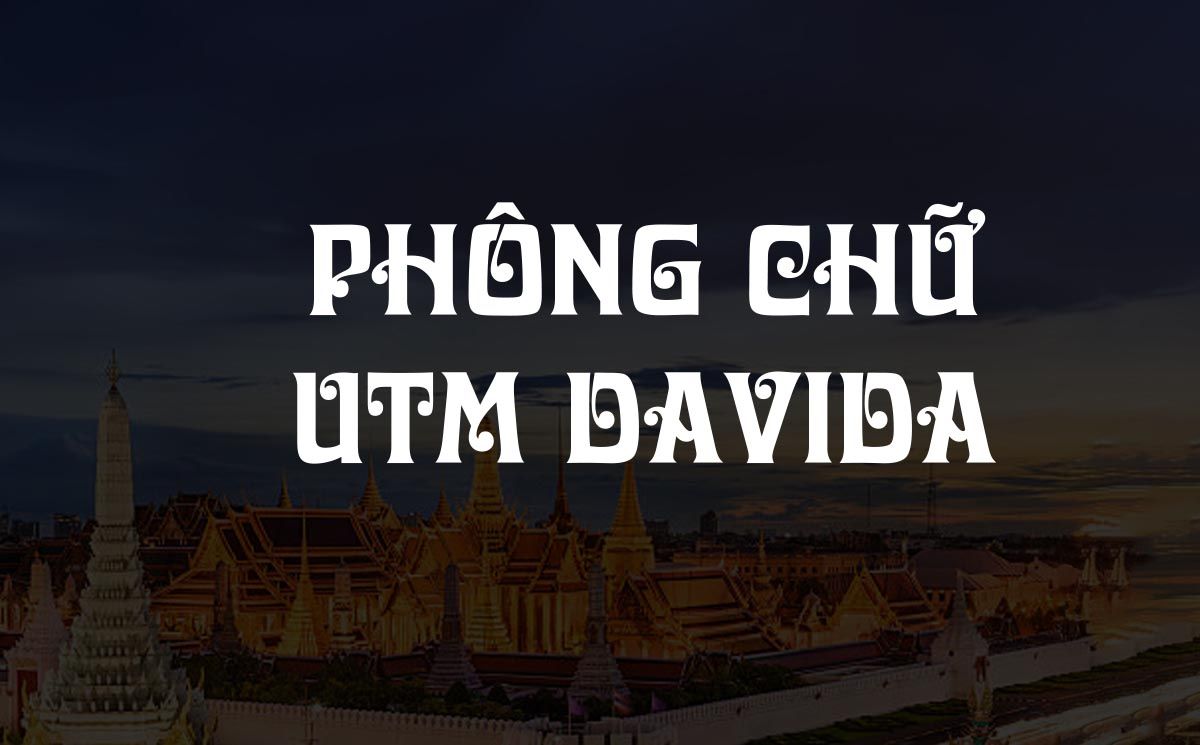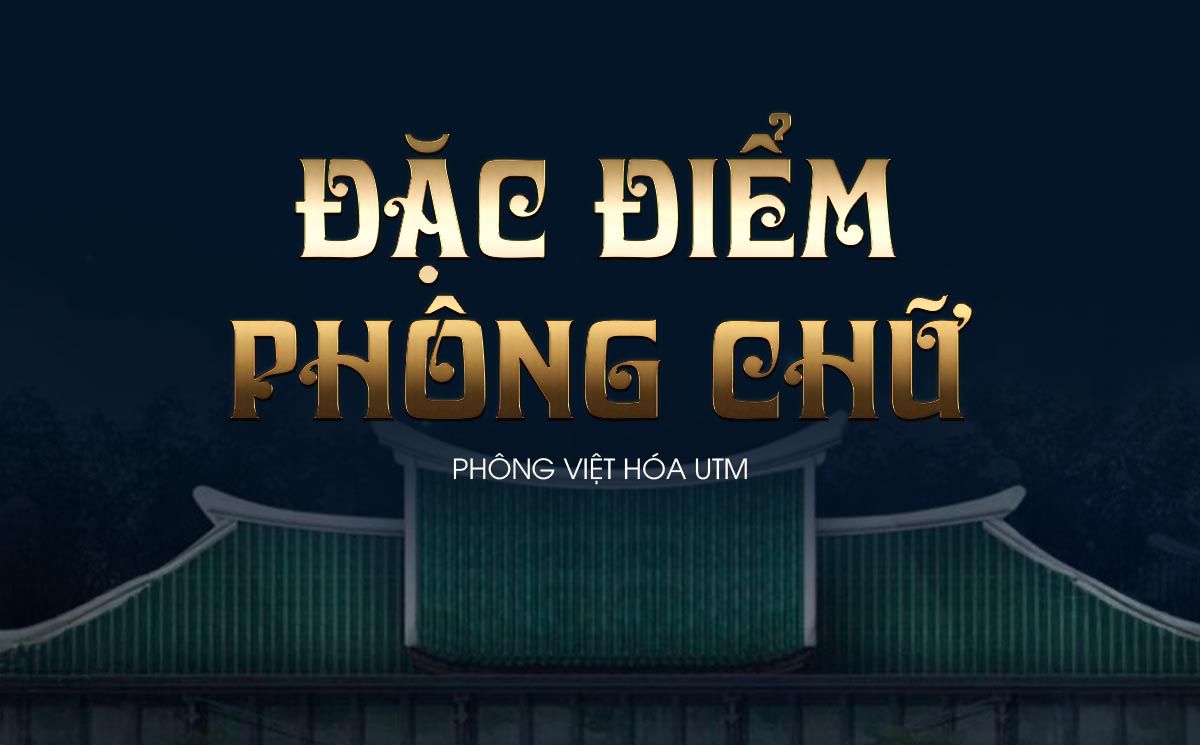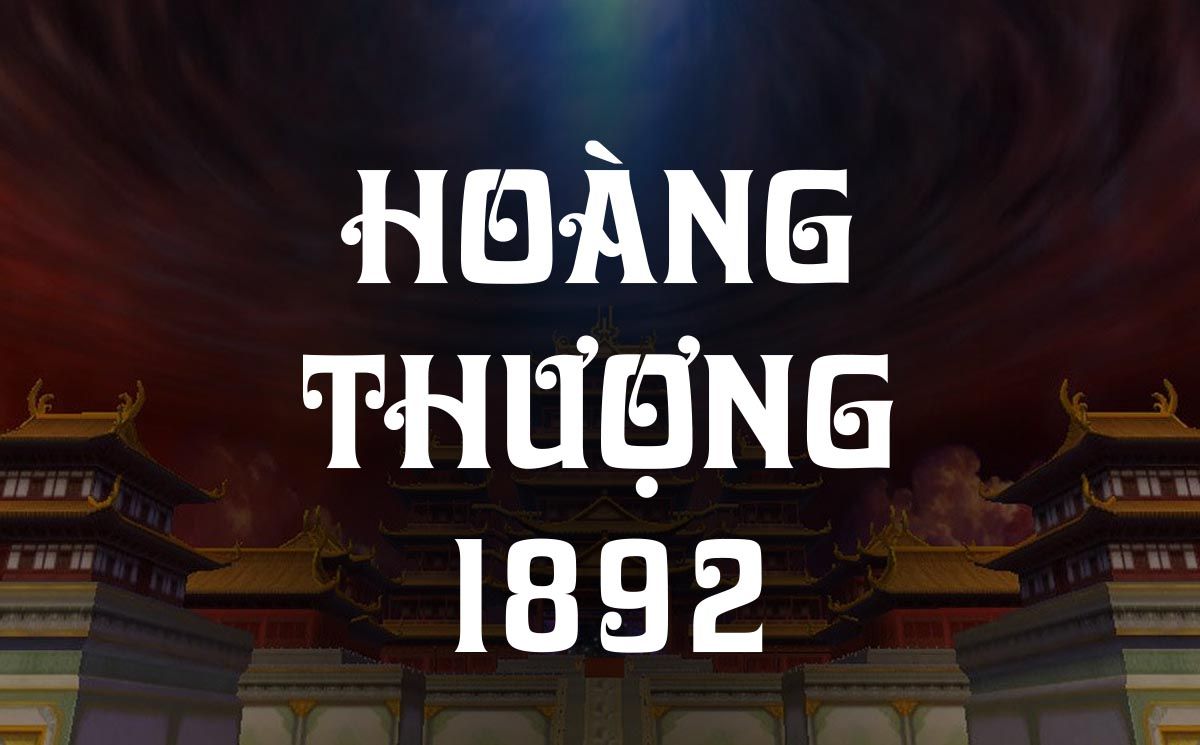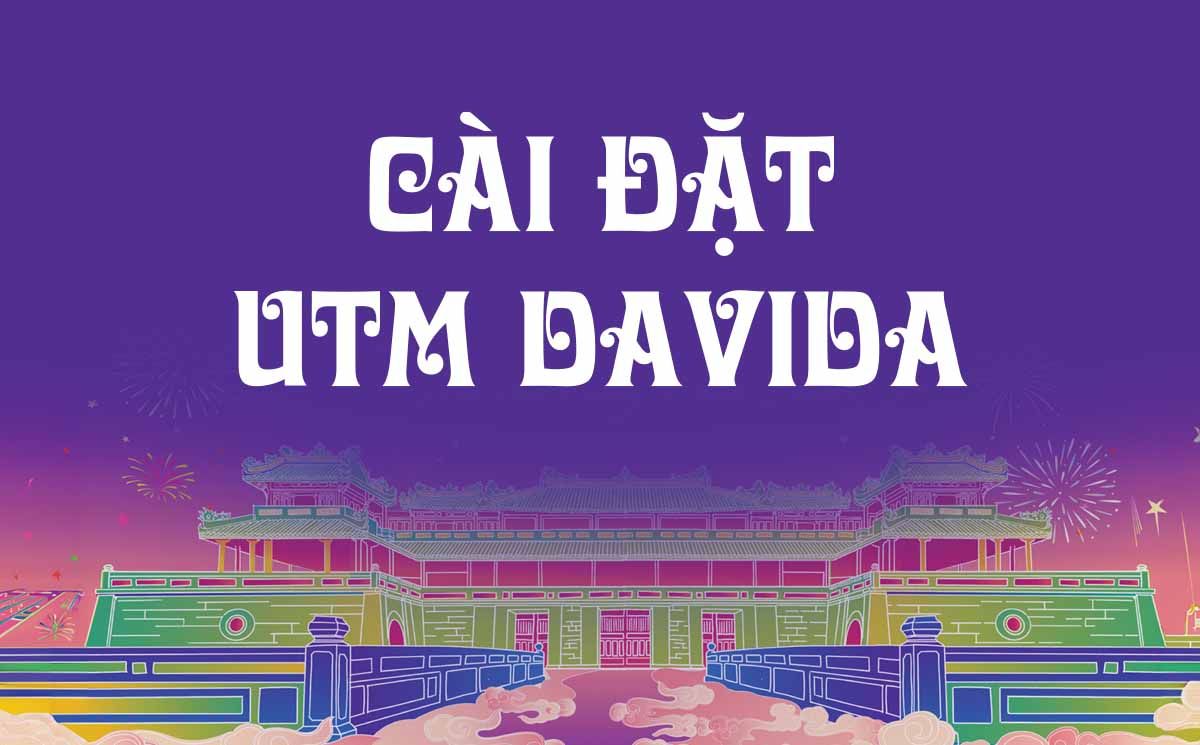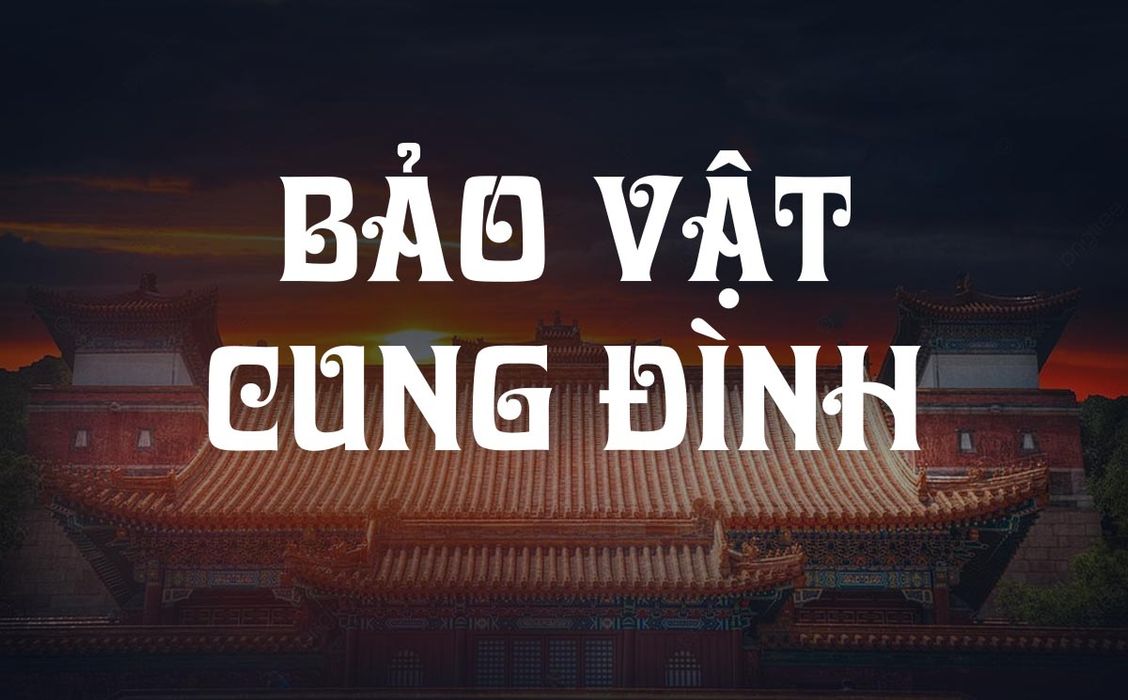
Font UTM Davida là một trong những kiểu font chữ serif Việt hóa nổi bật, mang đậm phong cách cổ điển và tinh tế. Được Việt hóa bởi nhóm Urban Type Management (UTM) – đơn vị uy tín chuyên chuyển thể các font chữ quốc tế sang phiên bản hỗ trợ đầy đủ tiếng Việt, UTM Davida không chỉ giữ trọn bản sắc thiết kế gốc mà còn tối ưu hóa cho người dùng Việt Nam.
Font được lấy cảm hứng từ kiểu chữ Davida nguyên bản (do David Harris thiết kế năm 1965), vốn nổi bật với các nét chữ uốn lượn nghệ thuật, thể hiện sự sang trọng và quý phái. Khi được Việt hóa, bộ font này trở thành lựa chọn lý tưởng cho các thiết kế cần tính trình bày cao như bìa sách, poster cổ điển, thiệp cưới, biển hiệu cửa hàng hay logo thương hiệu cao cấp.
UTM Davida thuộc nhóm serif cổ điển, với phần chân chữ rõ ràng, các đường cong mềm mại ở đầu và cuối nét tạo cảm giác hoài cổ và mang tính nghệ thuật. Font có sự tương phản mạnh giữa nét đậm và nét thanh, giúp tạo chiều sâu và tăng tính thẩm mỹ trong các phần tiêu đề, tên thương hiệu hoặc trích dẫn.
Ngoài ra, font đã được Việt hóa đầy đủ, hỗ trợ dấu tiếng Việt rõ ràng và mạch lạc, hoạt động tốt trên hầu hết các phần mềm thiết kế như Photoshop, Illustrator hay Canva. Điểm cộng lớn nữa là tính ứng dụng cao – bạn có thể dùng font này cho thiết kế in ấn hoặc kỹ thuật số, đặc biệt trong các dự án theo phong cách cổ điển, nghệ thuật hoặc sang trọng.
Font này là sự lựa chọn lý tưởng cho các designer chuyên thiết kế bìa sách, tạp chí cổ điển hoặc các sản phẩm mang tính trình bày cao. Những thương hiệu cao cấp hoạt động trong lĩnh vực thời trang, nước hoa, mỹ phẩm vintage cũng có thể khai thác tốt phong cách thanh lịch mà UTM Davida mang lại. Ngoài ra, chủ các spa, studio hay cửa hàng theo phong cách sang trọng cũng sẽ thấy font này đặc biệt phù hợp để làm bảng hiệu hoặc ấn phẩm quảng bá. Đối với những nhà thiết kế thiệp cưới hay thiệp mời sự kiện, font chữ này góp phần tăng thêm nét trang trọng và tinh tế cho thiết kế.